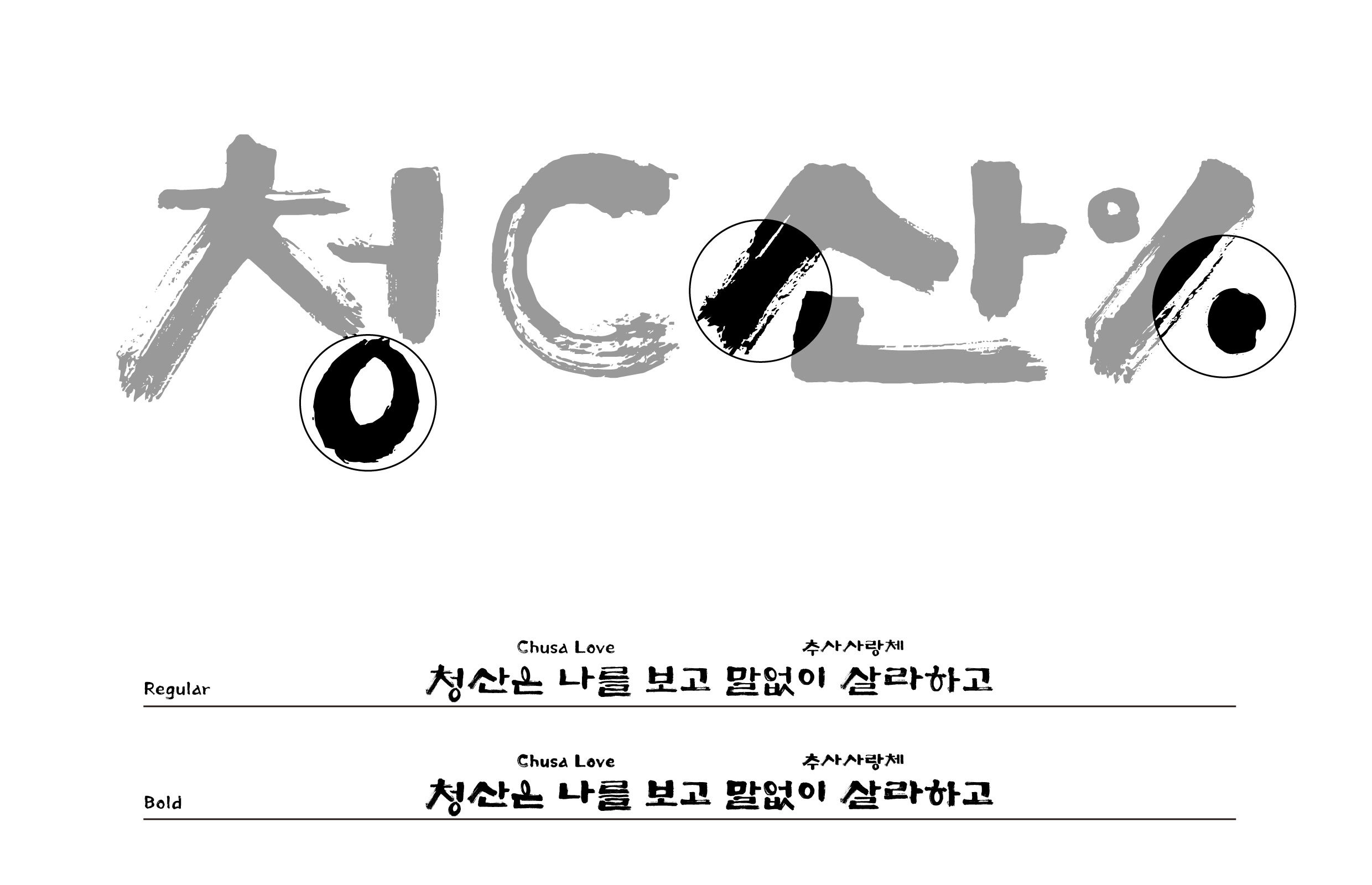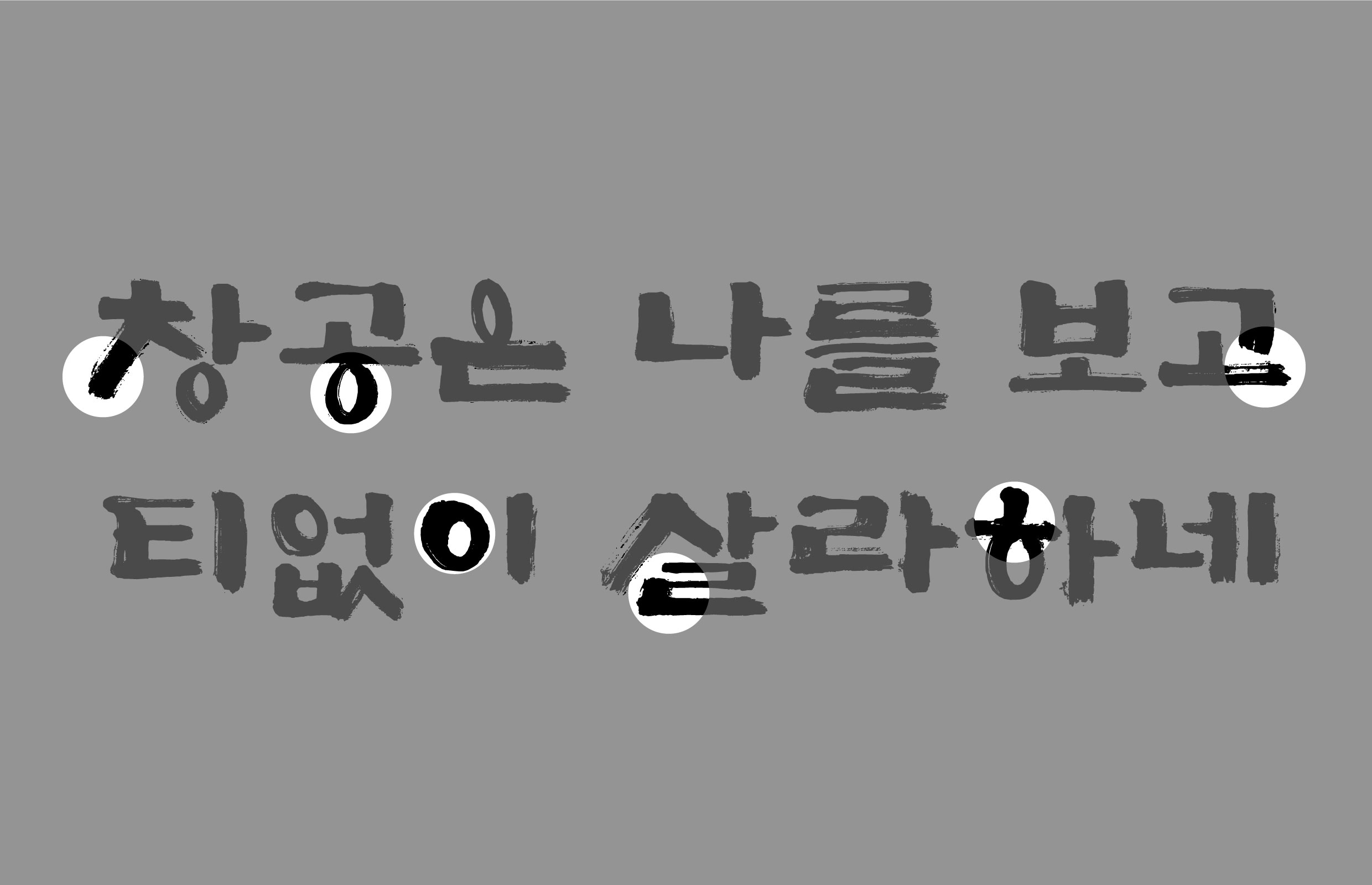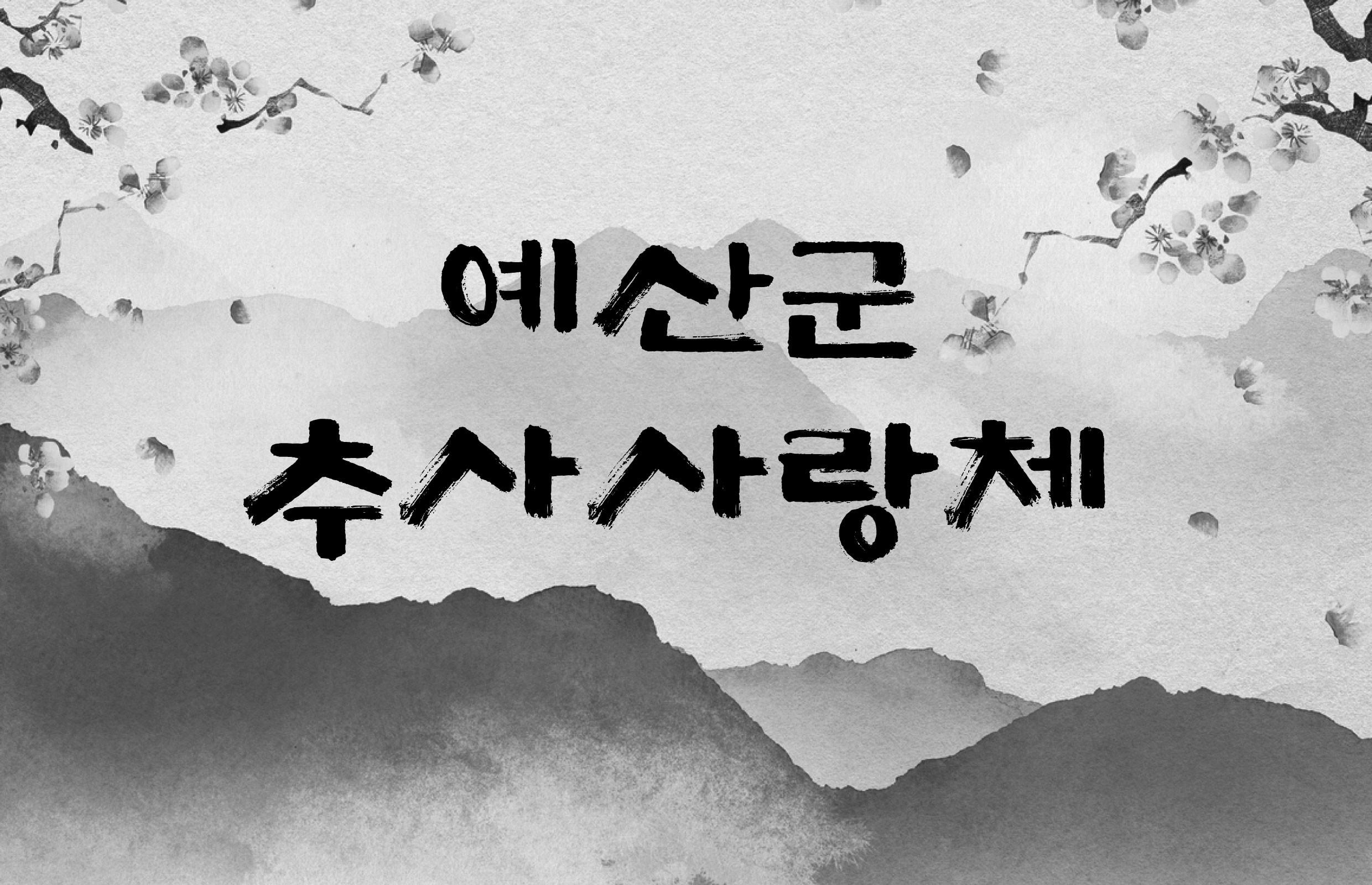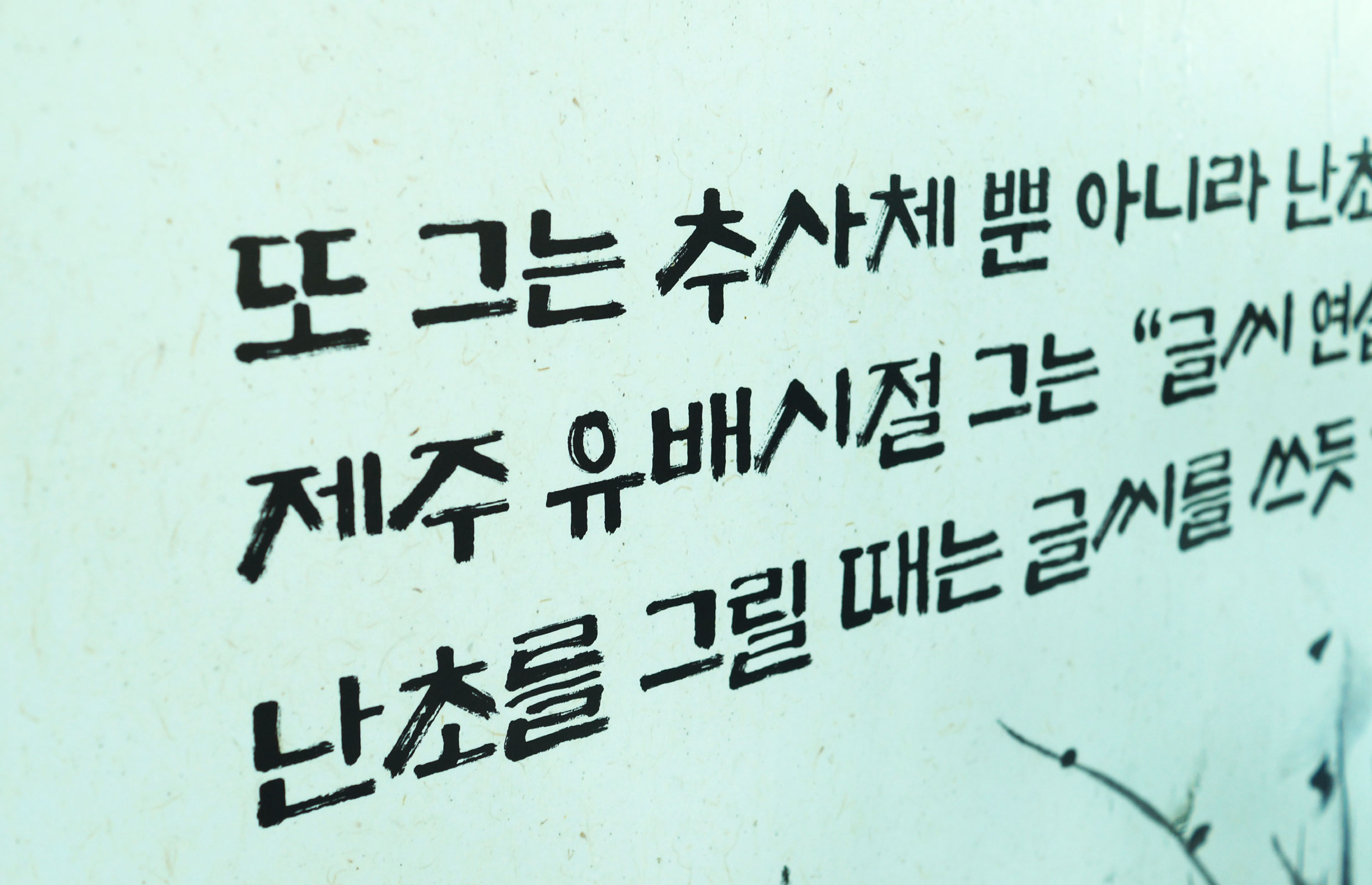
예산군
예산군 [추사사랑체]
추사 한글서체는 추사(秋史)체의 복원의 의미가 아니라 추사의 글과 그 뜻을 기리고, 이것을 현대적으로 해석하여 충남 예산의 새로운 아이덴티티의 지표를 수립하는 토대가 되기 위해 제작하였다. 추사 문화상품 및 지역 농식품의 이미지 제고, 관광산업사업은 물론 관련 홍보매체 등 다양한 분야에 활용되었다.